Шрифты для ASCII-таблиц и командной строки: что проверить
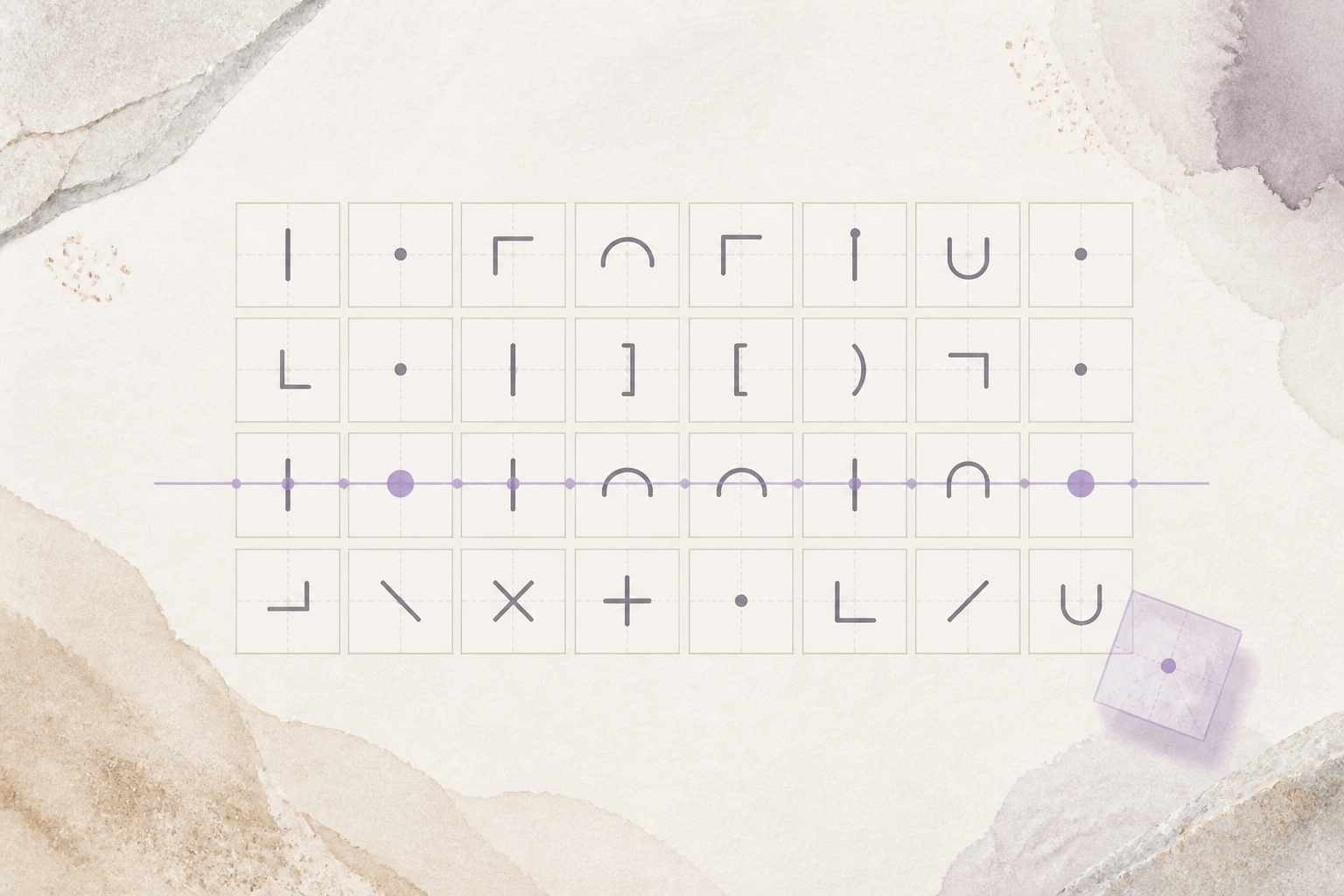
Для ASCII-таблиц и командной строки выбирайте моноширинный шрифт с предсказуемой шириной латиницы, кириллицы, цифр и знаков псевдографики. Затем проверьте Unicode, рамки, математические символы, комбинируемые знаки, контраст и отображение в целевых терминалах. Ниже приведён практический порядок проверки, примеры тестовых строк, чеклист и ответы на частые вопросы.
Почему терминалу нужен специальный шрифт
Командная строка отличается от обычного текстового интерфейса тем, что положение каждого символа влияет на структуру экрана. В таблице дата, статус или значение должны начинаться в одной и той же колонке. В логах важны одинаковые отступы, а в редакторах кода быстрый просмотр зависит от того, насколько легко различать символы. Поэтому основой служит моноширинный шрифт: каждый знак занимает одну и ту же базовую ячейку по горизонтали.
Терминологически ASCII и Unicode не одно и то же. ASCII содержит ограниченный набор базовых символов, включая латинские буквы, цифры и знаки пунктуации. На практике консольные таблицы часто используют Unicode-символы рамок, стрелки, маркеры, математические знаки и национальные алфавиты. Значит, шрифт должен быть не только моноширинным, но и достаточно полно покрывать нужный набор символов.
Что проверить в шрифте для командной строки
1. Настоящая ли это моноширинность
Моноширинность означает, что символы выровнены по сетке, а не просто выглядят похожими по ширине. У буквы I, цифры 1, точки и буквы M могут быть разные внутренние формы, но их advance width, то есть шаг продвижения курсора, должен оставаться одинаковым в пределах выбранного набора. Проверяйте не только латиницу, но и кириллицу, цифры, скобки, кавычки, слеши и знаки операций.
Для быстрой проверки наберите несколько строк одинаковой длины: WWWWWWWWW, iiiiiiiii, 111111111, МММММММММ и кириллическую последовательность. Добавьте таблицу с короткими и широкими визуально знаками. Если вертикальные разделители смещаются, проблема может быть в самом шрифте, в fallback-шрифте или в настройках терминала.
2. Поддержку кириллицы и нужных языков
Даже если основная работа ведётся с английскими командами, интерфейс терминала может содержать русские комментарии, сообщения об ошибках, имена файлов и данные из журналов. Проверьте заглавные и строчные буквы, ё, кавычки разных типов, дефис, тире, знак номера и валютные символы. Важно, чтобы кириллические глифы имели согласованные пропорции и не выбивались из латинской строки.
Отсутствующий символ обычно отображается пустым прямоугольником, вопросительным знаком или глифом из другого шрифта. Такой fallback может нарушить ширину строки и визуальный ритм. Проверяйте реальные данные, а не только короткий алфавит: добавьте названия файлов, пути, даты, смешанные латинско-кириллические идентификаторы и текст с пунктуацией.
3. Unicode и символы консольной псевдографики
Для рамок и разделителей используются символы Unicode box drawing: горизонтальные и вертикальные линии, углы, Т-образные соединения и перекрёстки. Они позволяют строить более аккуратные таблицы, чем набор из плюсов и дефисов, но предъявляют высокие требования к шрифту. Толщина линий, положение относительно базовой линии и соединение соседних глифов должны выглядеть единообразно.
Тестируйте не один угол, а полный набор комбинаций: верхняя, средняя и нижняя границы, пересечения, двойные линии и смешанные рамки. Полезный пример: ┌──────┬────────┐, затем строка с разделителями │ Имя │ Статус │ и завершение └──────┴────────┘. Если линии образуют разрывы, ступеньки или заметные утолщения, шрифт не подходит для плотных консольных таблиц.
4. Различимость похожих символов
В терминале особенно важны пары и группы, которые легко перепутать: ноль и заглавная O, единица и строчная l, латинская c и кириллическая с, латинская p и кириллическая р, дефис и длинное тире, обратный апостроф и кавычка. Хороший технический шрифт разводит такие формы за счёт перечёркнутого нуля, хвостов, засечек или разных пропорций.
Проверяйте также пароли, хэши, идентификаторы, версии пакетов и имена переменных. В этих строках ошибка чтения может привести не только к неудобству, но и к неправильному копированию команды. При этом чрезмерно декоративные формы ухудшают скорость сканирования, поэтому приоритетом остаются простые силуэты и ясные различия между знаками.
5. Контраст, размер и поведение на экране
Читаемость терминального шрифта зависит не только от рисунка букв. Проверьте его на малом размере, в обычном и жирном начертании, на тёмном и светлом фоне. Слишком тонкие штрихи исчезают при сглаживании, а чрезмерно плотные буквы сливаются в длинных строках. Межстрочный интервал должен позволять быстро переходить от одной строки лога к другой без ощущения сплошного серого блока.
Отдельно оцените курсор, выделение, подчёркивание и цветные статусы. У некоторых терминалов жирное начертание создаётся искусственно, поэтому тонкие детали могут становиться неровными. Если шрифт проектируется самостоятельно, заранее определите минимальный размер, основные веса и правила отображения на дисплеях с разным масштабированием.